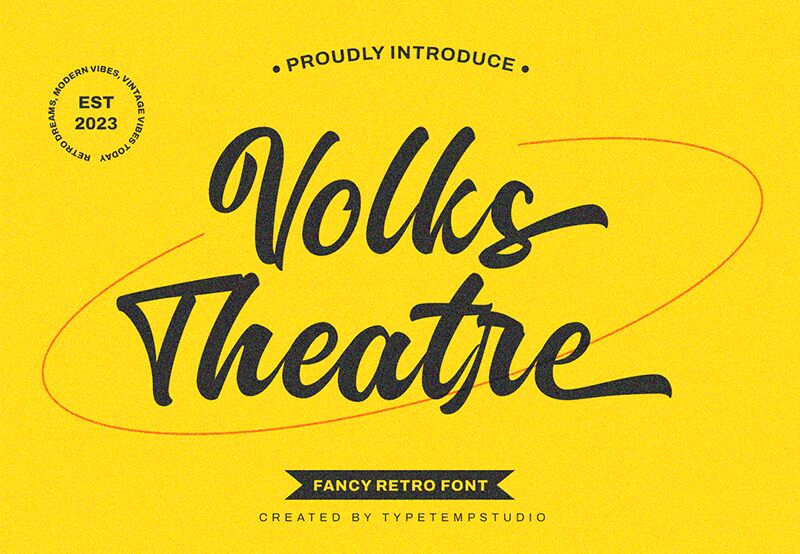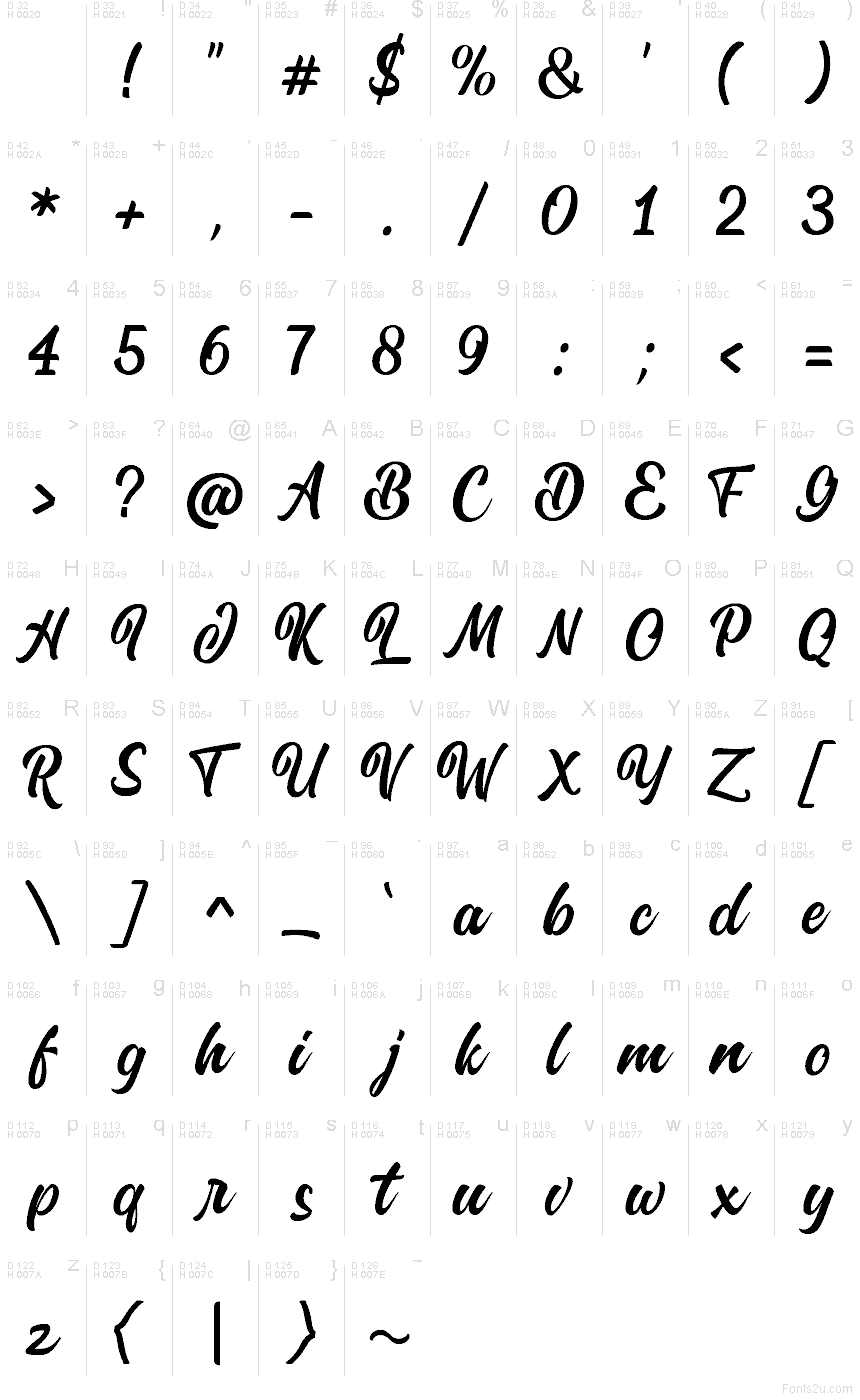
Volks Theatre est une police « brush script » gratuite de 2023, construite autour de lettres hautes et bouclées au style théâtral et dynamique. Les traits semblent peints d'un geste assuré, avec de longues courbes ascendantes, des jointures arrondies et un esprit rétro façon « signwriter » qui confère à l’ensemble une vitalité naturelle, loin des effets trop travaillés.
Elle est idéale pour des affiches, une identité visuelle de café, des pochettes de disques, des flyers événementiels ou des titres où une police gratuite pleine de mouvement et de caractère doit porter le visuel à elle seule. Utilisez-la pour des titres, des noms de packaging courts ou des initiales façon monogramme : ses boucles étendues et ses courbes compactes confèrent une gestuelle forte, même à quelques lettres seulement.